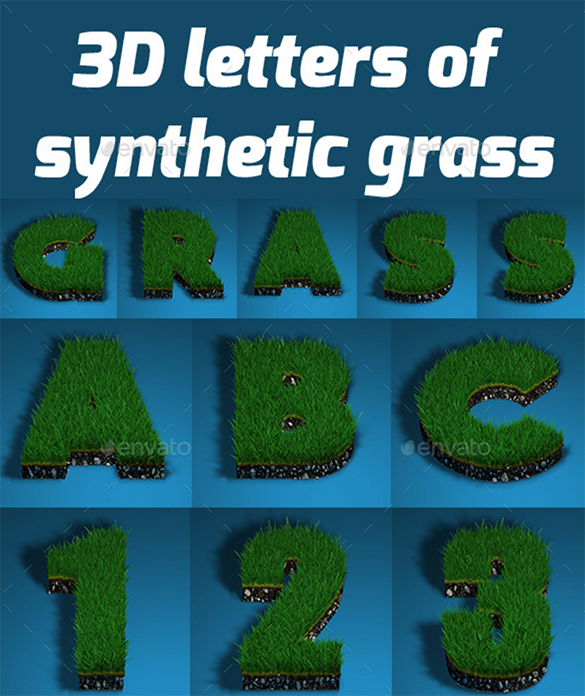
Crear pasto en 3D es genial, y más si creamos tipografía desde Cinema 4D. Por lo tanto les quiero compartir un genial tutorial para que aprendan a crear pasto.
Geniales herramientas como la de Hair y MoText son la esencia de este tutorial, agregando también los trucos de modificar el material de Hair para que tomen vida esas geniales hojas nacientes del suelo.
Realmente es vistoso para titulares, superficies y demás temáticas de la naturaleza. Creanme que es muy sencillo de aplicar.
Una genial forma el cual le he sacado provecho el haber aprendido esta técnica de crear pasto en tipografía desde Cinema 4D, es haber creado un alfabeto de pasto.
Como crear pasto en tipografía desde Cinema 4D
Agregar MoText al gusto y convertir el objeto en editable (tecla «c»), luego volvemos a convertir editables los objetos hijos de cada letra. Luego abrimos toda la jerarquía de objetos, hacemos una selección de estos y presionamos desde cualquier objeto de la ventana botón derecho, seleccionamos (Connect Objets + Delete).
Con la herramienta de seleccionar polígonos, seleccionamos las áreas donde queremos que se vaya a crear el pasto.
Después ya seleccionados, ir a menú Simulate/Hair Objets/Add Hair, de ahí en la ventana de Atributes seleccionando Hair y la pestaña de (Guides), configuramos el Length, Root (polygon center), Map (New).
En la pestaña de Hair (Counts: 30000), (Segments: 6), después en la pestaña de Fill Hair, activar y poner 2000.
Abrir Material editor, abrir el material de Hair, modificar colores al gusto. Bajar fuerza de especular. En Thickness (Root: 1.2), Variation 5 cm, en Curve, modificar el nodo final hacia abajo.
Activar Length al material y cambiar valores.
Por último activamos la opción de Frizz con los siguientes parámetros.
De ahí solo resta agregar materiales a las áreas donde no habrá pasto, así como configurar el render y agregar ambientación.